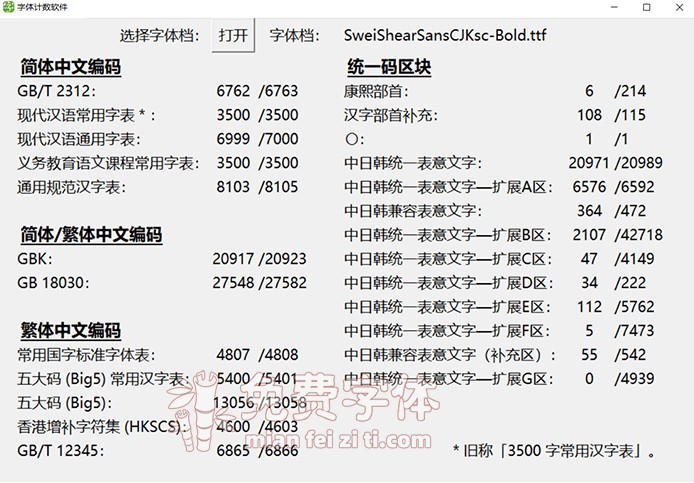
狮尾快剪黑体:Max造字 思源黑体笔触变斜和拔脚改造免费商用字体资讯
狮尾快剪黑体基于思源黑体的笔触变斜和拔脚改造,更加简明现代化的字体。支援简体中文、繁体中文、韩文与日文;可以免费商用,欢迎大家自由应用、自由优化、自由改作!
狮尾快剪黑体的特色是,修改原本是水平和垂直的线条为斜线,让字体比较有动感。